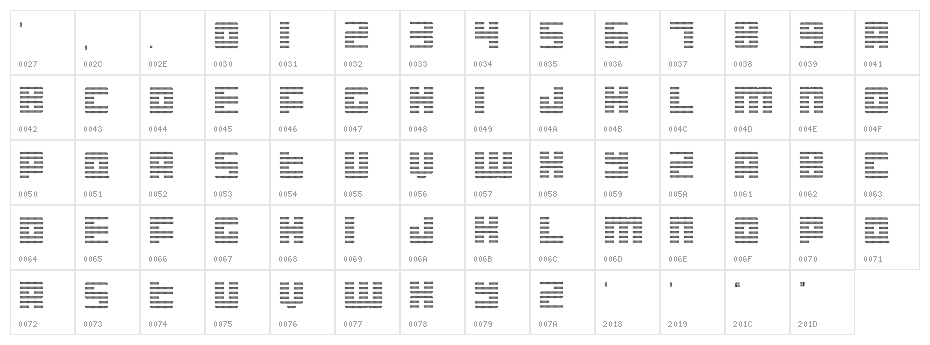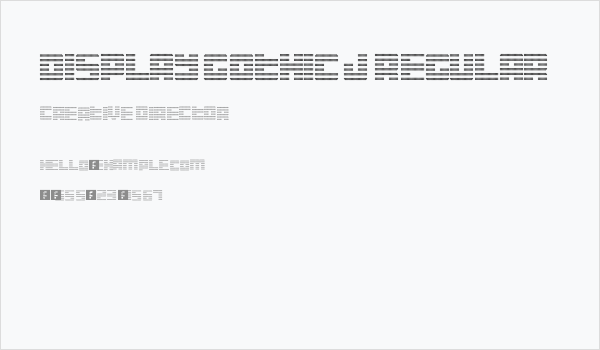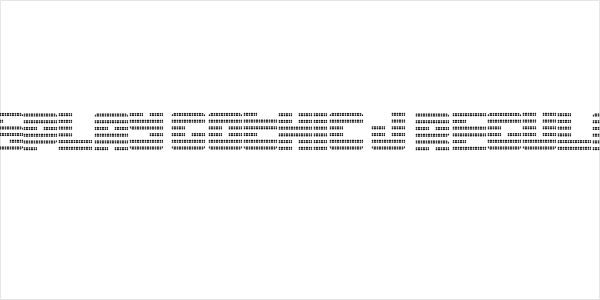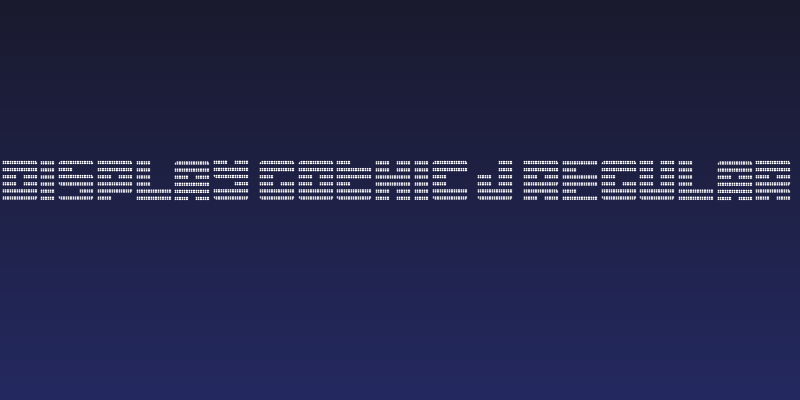
Display Gothic J Regular Font
| مشاريع مقترحة | Ideal for digital-themed projects, tech branding, futuristic posters, and any design requiring a modern, digital aesthetic. |
Display Gothic J Regular